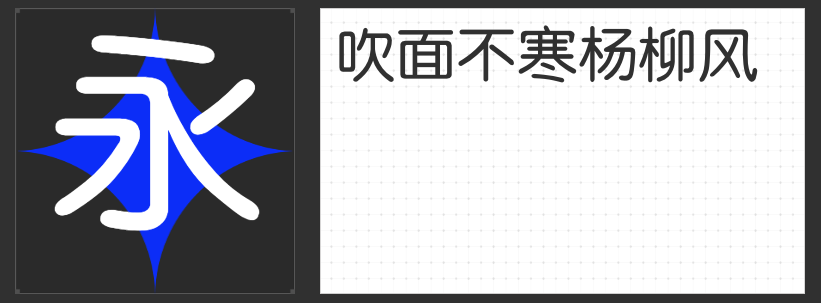
四款圆体设计字体推荐:以柔润笔触,勾勒视觉温度
在平面设计中,圆体字体以其柔和的线条与亲和力,成为品牌标识、包装设计及情感化内容表达的核心选择。相较于棱角分明的无衬线或传统宋体,圆体的曲线语言更能传递温暖、趣味与现代感。本文精选四款风格各异的圆体设计字体,从简洁明快到Q弹灵动,为设计师提供多元美学解决方案。
一、励字圆梦简 中黑
这款字体以直线与圆弧的巧妙融合打破传统圆体范式——笔画主体采用利落的直线,仅在起笔、收笔及转折处融入自然圆弧,形成“外圆内方”的独特结构。中宫松散的设计赋予字形呼吸感,避免视觉拥挤,同时保留宋体字骨的端正气质。其简洁的竖折笔画替代部分弧线,既保留圆体的柔和感,又提升小字号下的识别度,适合需要兼顾专业感与亲和力的品牌视觉系统。
二、字圈也字多肉体
“破方为圆”是这款字体的核心设计哲学——所有笔画转折均以充满流动感的圆弧替代直角,甚至通过封闭圆环的创意处理,让字形产生如气泡般的轻盈感。圆润饱满的笔形搭配适度的字面扩张,营造出Q弹可爱的视觉效果,传递出无攻击性的温暖气质。其灵动的曲线语言尤其适合儿童品牌、文创产品及社交媒体内容,为信息传递注入趣味基因。
三、励字粗圆简繁
相较于纤细圆体,这款字体以粗笔画与方正结构构建视觉重量感。笔形柔和却无冗余装饰,字面较大且中宫紧凑,确保远距离识别性。外轮廓的圆角处理削弱了粗字体的笨重感,反而传递出端正大方的稳重气质。其繁简同体的设计更满足多语言场景需求,适合作为科技、教育等领域品牌的主标字体,平衡专业性与人文温度。
四、励字准圆简繁
以无衬线设计逻辑重构圆体美学,这款字体通过笔画粗细一致与边角圆弧处理,打造出清新整齐的视觉秩序。中细笔画赋予字形轻盈呼吸感,而精准的几何结构则确保阅读流畅性。其简约风格既可独立作为正文排版字体,亦能通过大小、色彩对比成为标题焦点,尤其适合追求极简美学的时尚、生活方式类品牌设计。
圆体字体的魅力,在于以曲线语言消解视觉距离感,同时通过结构、笔画粗细的变化传递多元情绪。这四款字体均以独特设计语言拓展了圆体的应用边界,为设计注入温度与生命力。